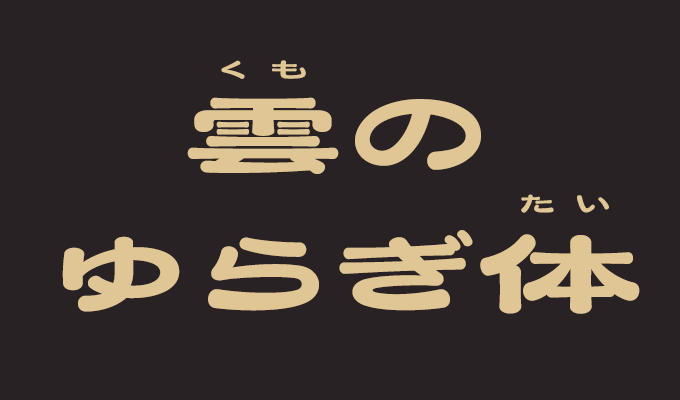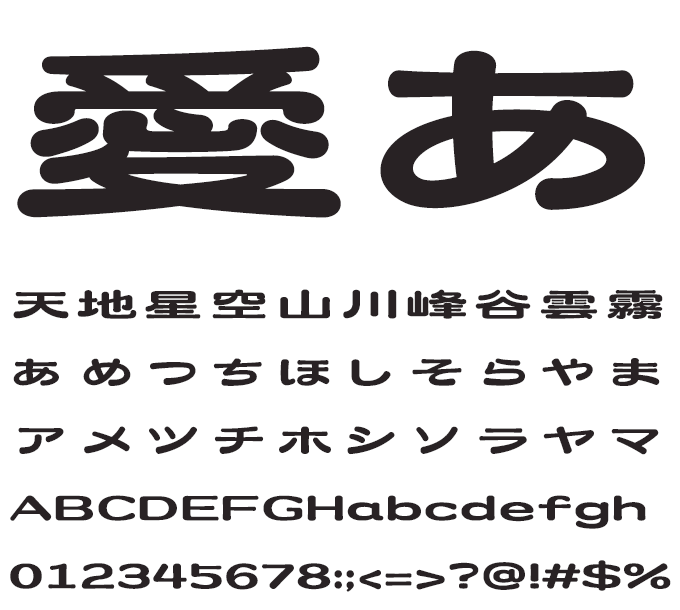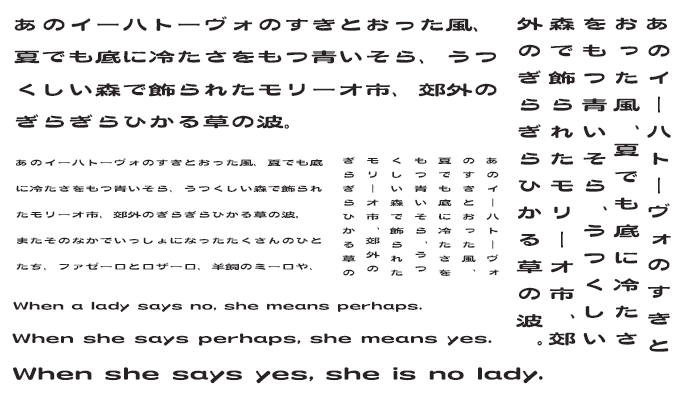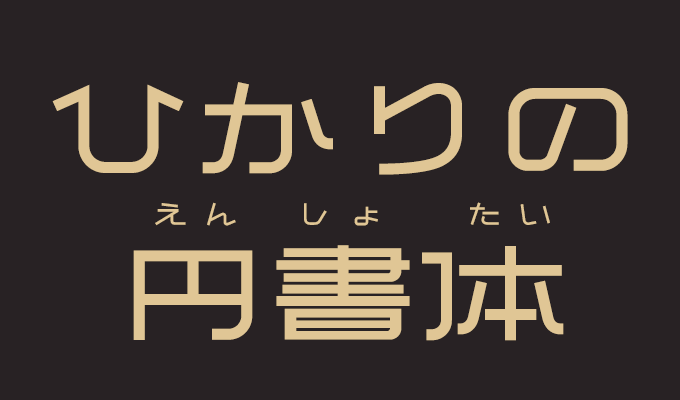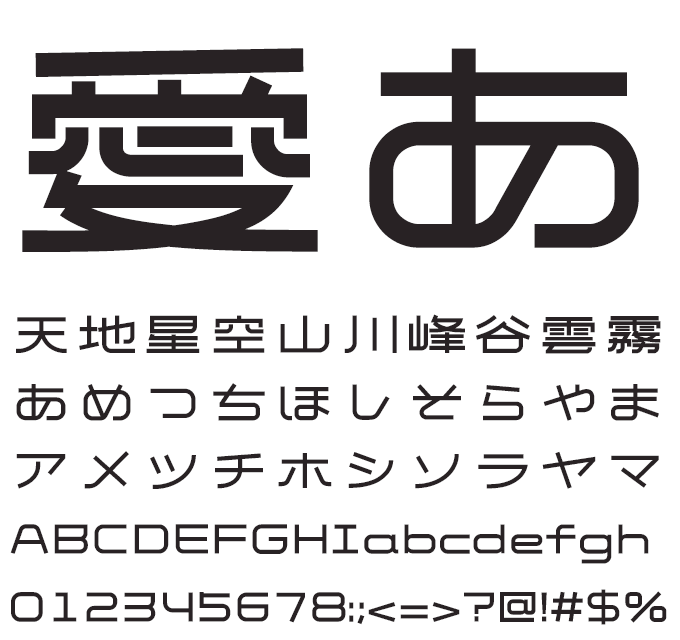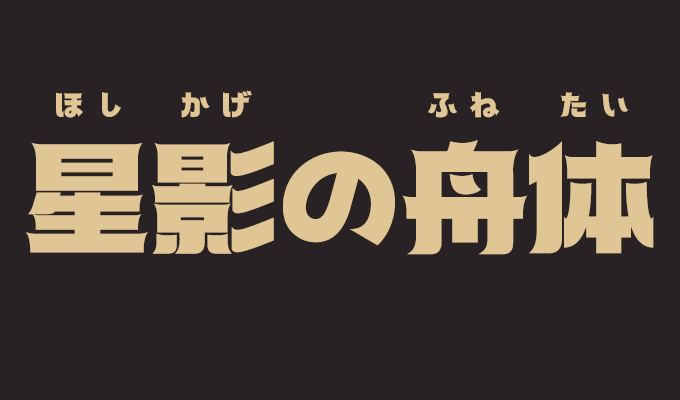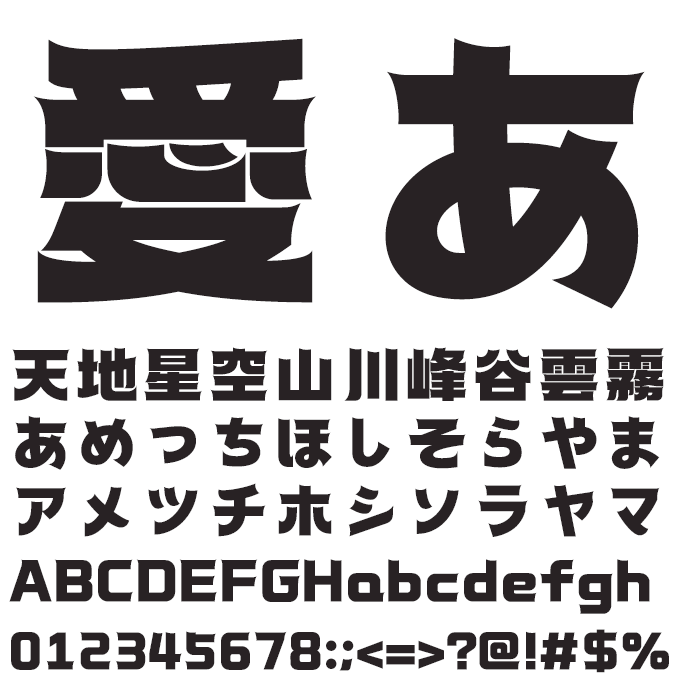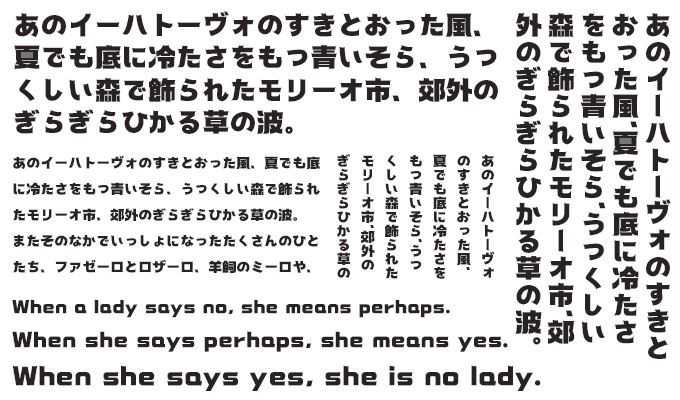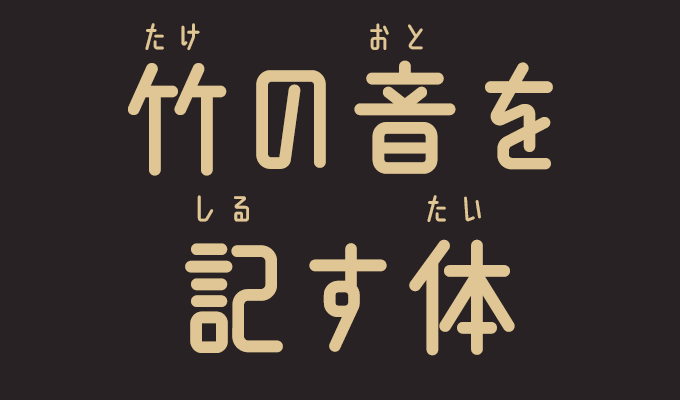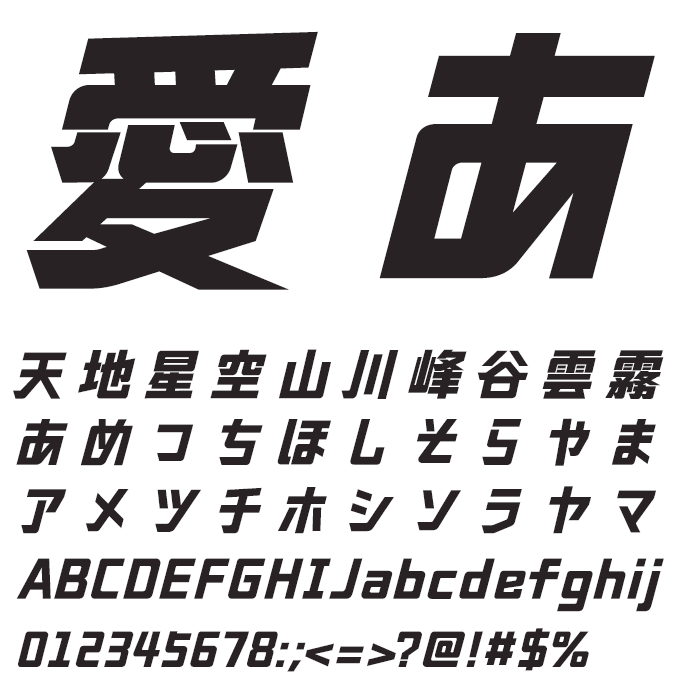
自由な発想から生まれる 楽フォント
異なる文化の美的な特徴と伝統を融合したフォントブランド「楽フォント」
『フォントを通して繋がるすべての人が気楽に楽しめるように、文化の多元的要素を含むフォントの創作で、文字による彩りを日常にもたらす』を理念に掲げる楽フォント。現在も新作の開発が続いており、斬新でありながら異なる文化の美的な特徴と伝統を融合した全45書体が販売中です。そんな楽フォントの書体たちをご紹介します。
楽フォントとは?
斬新な日本語書体で新しい価値を生み出すため、2017年に国内外のデザイナーで開発チームを結成。異なる文化の美的な特徴と伝統を融合した書体をコンセプトとし、約3年間に渡り開発。2020年に法人化し、厳選したフォントをリリース。
様々な実績を持つデザイナーチームが作り出す多元なフォントは、情報伝達と文化の次元を超え、人と人の心や想いを繋げ、楽しませながらその価値を最大限に発揮します。
フォントを通して楽しいコミュニケーション社会の実現を目指す、楽フォントの今後にご期待ください。
デザイン誌にも掲載され注目も高まっています
Communication Arts11/12月号【Advertising Annual】
コミュニケーションアーツ主催2021 Advertising部門に、楽フォント書体の楽しさ・優美さを紹介したプロモーションビデオが入賞。プロモーションビデオでは玲優体・親剛体・書房体・書房体H・明朗体・文尚体・喜縁体を使用。
idea (アイデア) No.395 [2021/9/10発行]
文化を築く装飾系フォントの世界 楽フォントの書体づくり vol. 4
2021年秋リリースの5書体をご紹介。グラフィックデザイナーの加瀬透が装飾書体とグラフィック表現の可能性を探る。
idea (アイデア) No.392 [2020/12/10発行]
文化を築く装飾系フォントの世界 楽フォントの書体づくり vol.1
楽フォントの書体づくりについてのインタビュー記事が掲載されています。
楽フォントのコンセプト
国内外のデザイナーによる多元なデザイン
国内外のデザイナーで結成された開発チームによって、異なる文化の美的な特徴と伝統を融合をコンセプトに作り出されています。斬新でありながら懐かしさもある多元なラインナップになっています。
豊富な収録文字数
楽フォントの各書体はいずれも、日常用途に十分な漢字と記号を収録するAdobe-Japan1-3対応。
JIS第一・第二水準漢字はもちろん、いわゆる機種依存文字とされることもある「はしご高」「立ち埼」なども利用できます。
オススメの使い方
桜と少女体
森と動物体
縁摩体・黒基体・閃刃体
辿秀体
兎天体・書房体H
喜縁体・芽明体
熊ちゃん体・彩圓体
友人からの手紙体・雨上がりのお茶体
玲優体 (れいゆうたい)
面相筆で描いたような筆使いが特徴的な書体。細長くスマートな字面は優美ですが、点部分に円形デザインを採用し、心地いいアクセントに。
親剛体 (しんごうたい)
縦画と横画の線幅のコントラストによって生み出される圧倒的存在感と、滑らかでやわらかいカーブの調和が特徴。重量のある密度の高いデザインでも、高い可読性を保っているのがポイントです。
書房体 (しょぼうたい)
古代書体の優美な上品さを纏った、シャープな線が現代的でモダンな印象の書体。個々の文字の中にユーモアのあるアクセントを施し、抑揚ある文字組を演出します。
書房体H (しょぼうたいH)
書房体に施した趣向を保ちながら、ウェイトを重くしました。繊細なデザインワークを、より鮮明に。
明朗体 (めいろうたい)
筆を勢いよく抜いたようなエッジの効いたハライと、力強く墨溜まりを作ったトメの表現がバランスの良い緩急を生みだしています。
文尚体 (ぶんしょうたい)
直線的設計によるコンパクトな堅牢さと、優しいアーク化エレメント。短めの横線は斜めにデザインし、スマートな中にもより印象的な刺激を。
喜縁体 (きえんたい)
文字のトメ・ハネが跳ね上がるようなデザインは文字組みをポップで明るく、楽しげに。リズミカルで、活力のある書体ですが、統一感を持ち安定した設計です。
縁摩体 (えんまたい)
どこかの街角で、いつかの作品で、縁が摩耗するほど時が経っても、存在感と可読性を失わない文字たち。存在感を放つウエイトと、可読性。
岩曙体 (がんしょたい)
まぶしい朝日で輪郭が欠けた岩をイメージしました。オーソドックスなゴシック体を基調とした岩のような素朴さと裏腹に、ポップなシーンにも馴染む安定感。
蛍涼体 (けいりょうたい)
蛍の舞う川辺のように、涼しい面持ち。特徴的なうろこや点、はらいが新鮮で、含む空気はどこまでも爽やかな書体です。
遊妖体 (ゆうようたい)
ユニークなあそび心満載のアクセントが妖しく戯れる、楽しくも幻想的な書体です。見出しとなる場所でひときわ魅力的に、印象的に。
凛松体 (りんしょうたい)
凛々しい佇まいの黒松から着想を得ています。ダイナミックなウエイト表現にモダンなエッジを加えて、端正な面持ちの中にもしっかりとした芯が感じられる書体です。
黒基体 (こっきたい)
細部のデザインでは復雑な特徴をつけず、基本に戻った文字本来の素朴さと美しさを楽しめるような設計を施しています。
兎天体 (うてんたい)
字面率が抑えられた設計のため全体的にやや小ぶりですが、生き生きとした筆遣いや、トメ・ハネ・はらいが軽やかなユーモアに富んだ書体です。